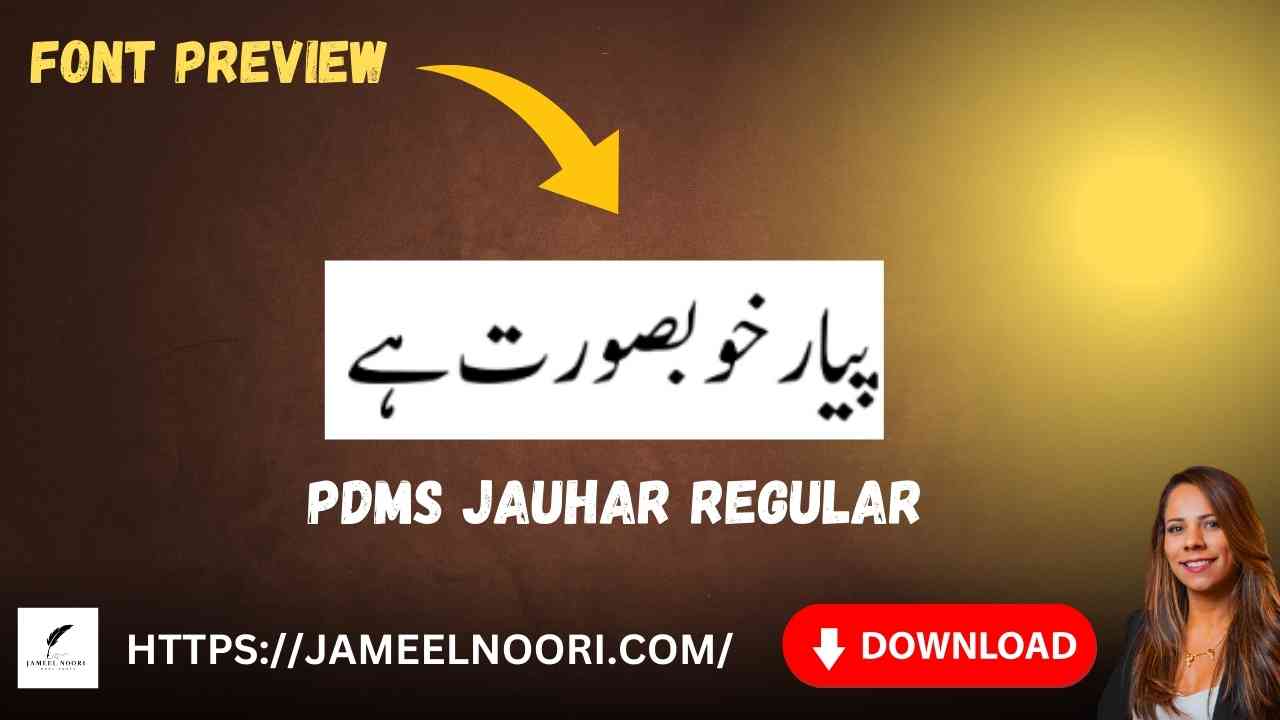
Introduction – Download Urdu font PDMS Jauhar Regular
Aaj kal Urdu likhne ke liye best Urdu fonts ki demand Pakistan mein bohot zyada barh gayi hai. Inhi fonts mein se ek mashhoor aur reliable font hai Download Urdu font PDMS Jauhar Regular. Ye font specially un users ke liye design kiya gaya hai jo Urdu typing, designing aur publishing ke liye readability aur beauty ko importance dete hain. Iska stylish aur clear design students, teachers, bloggers aur designers ke liye ek perfect choice banata hai.
Features of PDMS Jauhar Regular Urdu font
Download Urdu font PDMS Jauhar Regular ki kuch khas features yeh hain:
- Smooth aur clean Urdu Nastaleeq style.
- Perfect for books, articles, aur websites.
📌 Agar aap Urdu likhne me readability aur professional look chahte hain to ye font best choice hai.
Benefits of Using Download Urdu font PDMS Jauhar Regular
Download Urdu font PDMS Jauhar Regular use karne ke fayde:
- Urdu documents aur designing ka look improve karta hai.
- Multiple platforms ke sath compatible hai.
- Students aur professionals dono ke liye best choice hai.
Why People in Pakistan Prefer Download Urdu font PDMS Jauhar Regular
Pakistan me Urdu likhne aur publishing ke liye PDMS Jauhar Regular widely use hota hai. Iski affordable aur easy-to-use qualities isse zyada popular banati hain. Designers aur bloggers ko ye font pasand hai kyunki iski readability high hai.
Conclusion – Download Urdu font PDMS Jauhar Regular
Agar aapko Urdu font chahiye jo free, best aur easy-to-use ho to Download Urdu font PDMS Jauhar Regular aapke liye ultimate option hai. Ye font Pakistan me Urdu typing aur designing ke liye expert choice mana jata hai.